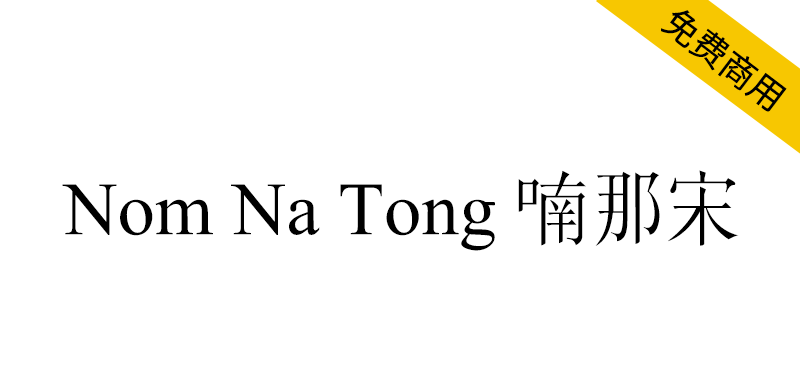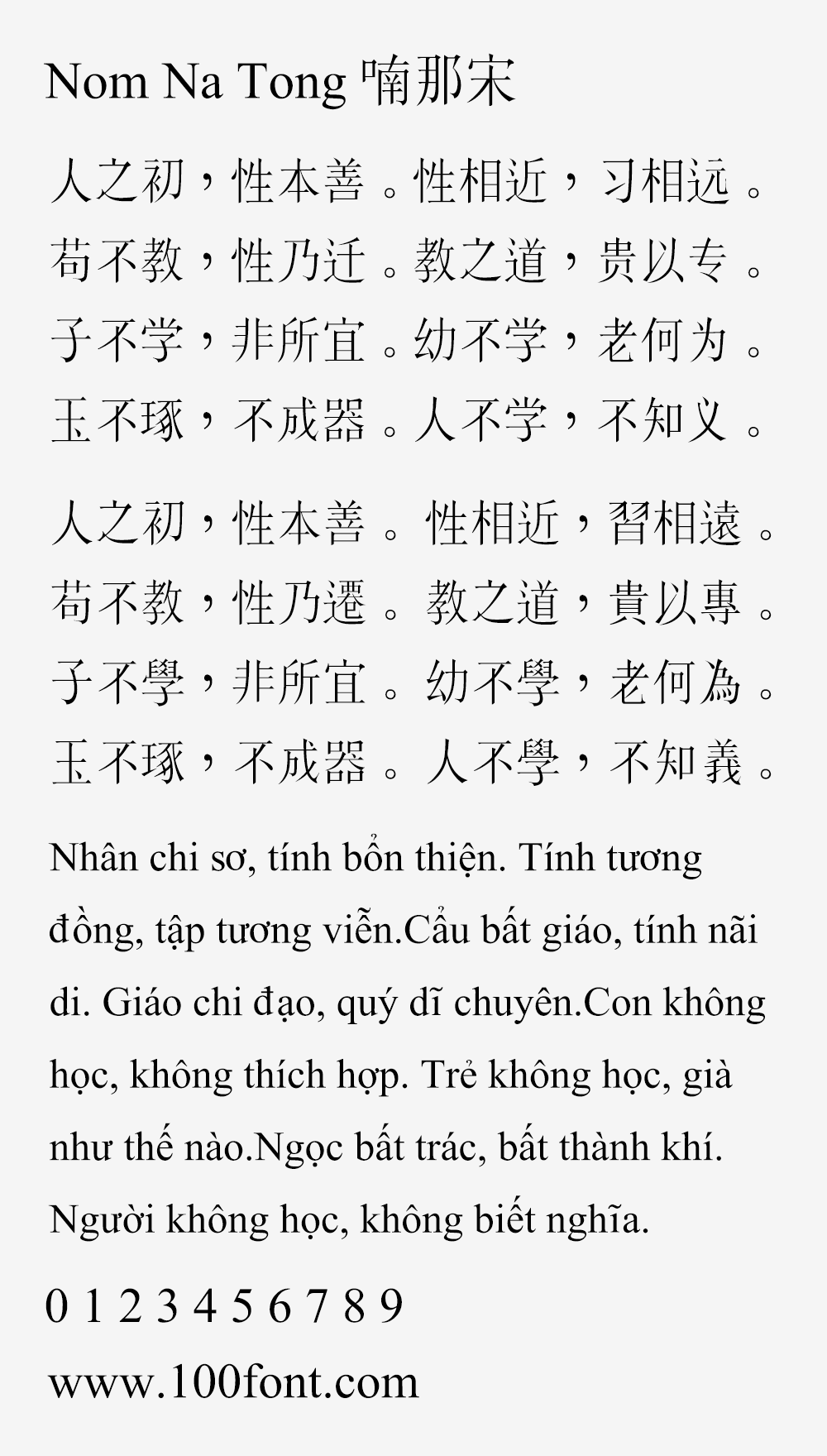
这是“Nom Na Tong”字体的存储库。Nom Na Tong字体最初是在越南Nôm保护基金会的赞助下开发的http://www.nomfoundation.org,成立于1999年。该字体的开发既是以Unicode编码越南Hán-nôm文字的建议的最终来源,也是促进使用该文字书写的作品遗产的途径。该字体目前包含26000多个字形,代表了学者、软件工程师和其他专家的集体工作。它仍然是正在进行的Unicode编码Hán-nôm工作的参考字体。该基金会于2018年底解散。现在,该字体是作为一个开源项目提供的,希望对保存Hán-nôm脚本感兴趣的社区能够继续维护和扩展它。
This is the repository for the "Nom Na Tong" font. The Nom Na Tong font was originally developed under the aegis of the Vietnamese Nôm Preservation Foundationhttp://www.nomfoundation.org, established in 1999. The font was developed both as a definitive source for proposals to encode the Vietnamese Hán-Nôm script in Unicode and to promote access to the heritage of works written in that script. The font currently contains over 26,000 glyphs, and represents the collective work of scholars, software engineers, and other experts. It continues to be the reference font for the on-going work of encoding Hán-Nôm in Unicode. The foundation dissolved at the end of 2018. Now the font is being provided as an open source project in the hope that a community of those interested in the preservation of the Hán-Nôm script will continue to maintain and extend it.